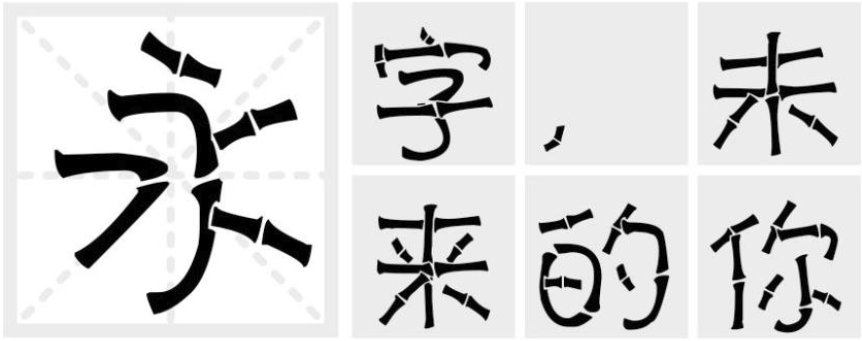
汉仪竹节体是一款极有个性的电脑简体中文创意字体,其特性是每一个中国汉字看上去都像毛竹一样 ,字体设计风格与众不同 ,字的笔画神似自然界中的圆竹形状 ,字形中的点、撇、捺、钩、提等笔画各具面目,笔画运用了竹节图形元素来构建,把这些笔画做成了竹节,粗大强健 ,苍劲有力。并且使左右舒展的笔画尽量对称,最大限度地简化笔画竹节造型。